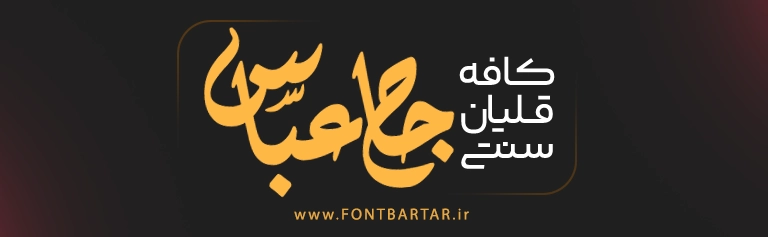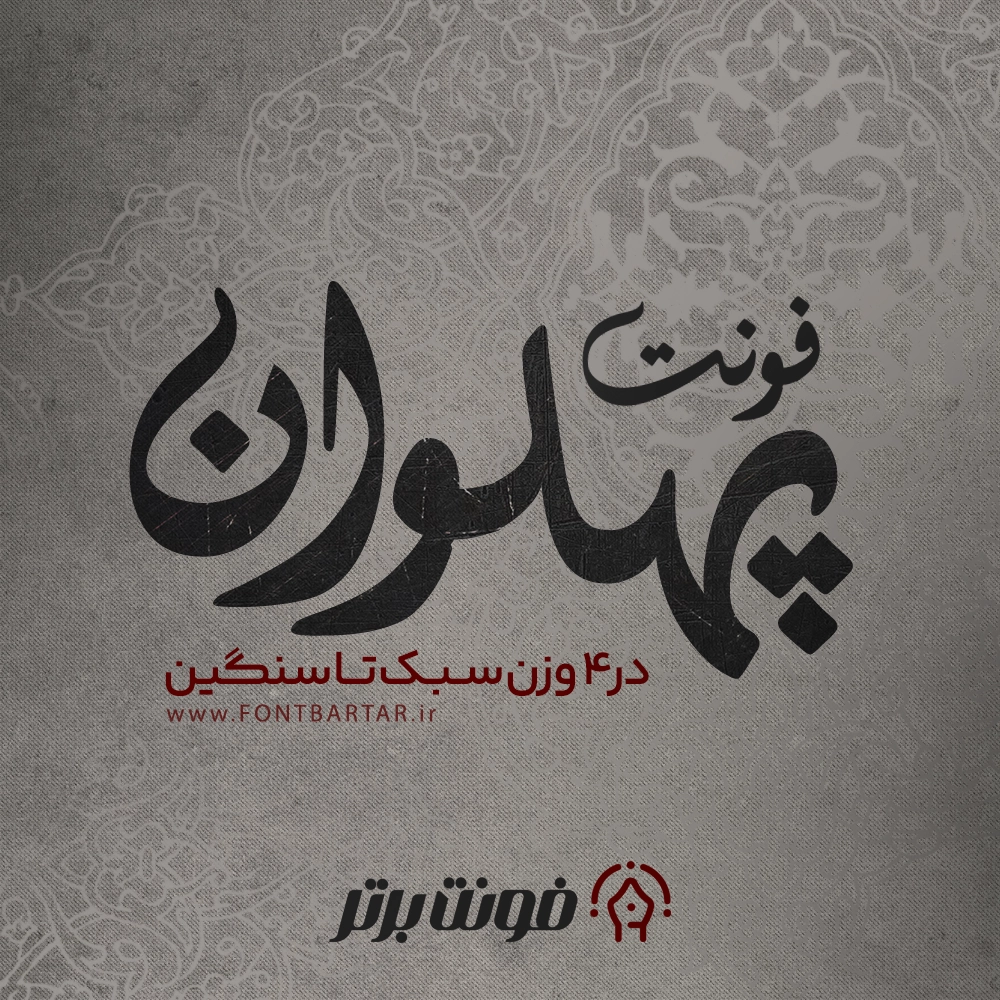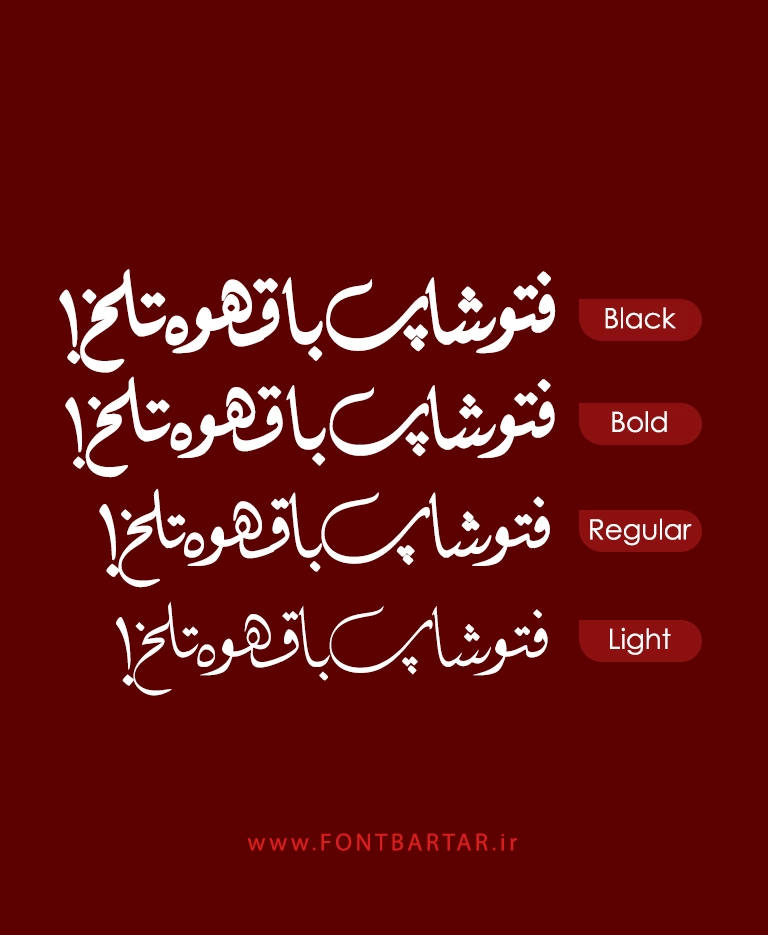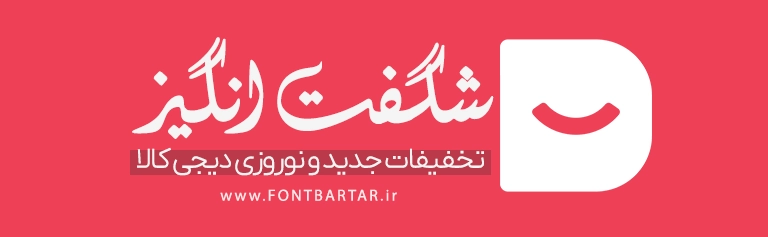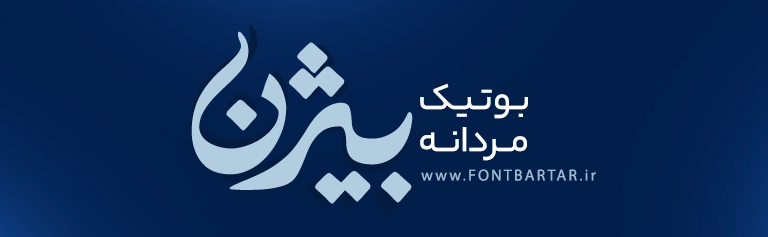
دانلود فونت فارسی پهلوان | فونت نستعیلق و زیبا برای طراحی خاص
فونت فارسی پهلوان یک فونت فارسی خاص ، سنگین و چشمگیر است که با الهام از تایپوگرافی سنتی و حس قدرت و صلابت طراحی شده است. فونت فارسی برای فتوشاپ انتخابی عالی برای طراحانی است که به دنبال ایجاد حس اقتدار، اصالت و هویت قوی در پروژههای گرافیکی خود هستند. اگر قصد دارید در طراحی پوستر، کاور، تایپوگرافی یا برندینگ، توجه مخاطب را در اولین نگاه جلب کنید، فونت زیبا پهلوان یکی از بهترین گزینههاست.
معرفی کامل فونت پهلوان و سبک طراحی آن
خرید فونت فارسی پهلوان دارای ساختاری سنگین، پرقدرت و نمایشی است که بهخوبی برای پروژههای خاص و جسورانه کاربرد دارد. ترکیب خطوط ضخیم با فرمهای سنتی باعث شده این فونت حس حماسی و ماندگاری بالایی ایجاد کند.
خرید فونت ویژگی برجسته فونت پهلوان:
- طراحی الهامگرفته از تایپوگرافی سنتی فارسی
- مناسب تیترها و نوشتههای نمایشی
- فونت نستعلیق پهلوان خوانایی بالا در سایزهای بزرگ
- جلوه بسیار قوی در تایپوگرافی هنری
فونت جدید پهلوان در ۴ وزن سبک تا سنگین
دانلود فونت در ۴ وزن استاندارد ارائه شده است تا طراح بتواند بسته به نیاز پروژه، انتخاب دقیقتری داشته باشد. تنوع وزنها امکان استفاده در طراحیهای مختلف را فراهم میکند؛ از تیترهای سنگین تا نوشتههای شاخص.
کاربرد وزنها:
- تیتر و هدینگ پوستر
- تایپوگرافی هنری و مذهبی
- طراحی کاور شبکههای اجتماعی
- لوگوتایپ و هویت بصری برند
کاربردهای فونت فارسی پهلوان
فونت پهلوان انتخابی ایدهآل برای پروژههایی است که نیاز به حس قدرت و جدیت دارند:
- طراحی پوستر فرهنگی، مذهبی و حماسی
- تایپوگرافی نام و شعار
- طراحی لوگو و لوگوتایپ فارسی
- کاور اینستاگرام و بنر تبلیغاتی
- پروژههای چاپی و دیجیتال
چرا فونت نستعلیق پهلوان برای طراحان حرفهای مناسب است؟
دانلود فونت نستعلیق پهلوان به طراحان کمک میکند تا بدون نیاز به طراحی دستی حروف، به یک فونت آماده با هویت بصری قوی دسترسی داشته باشند. این موضوع باعث صرفهجویی در زمان و افزایش کیفیت خروجی نهایی میشود.
مزایای اصلی فونت نستعلیق :
- سرعت بالا در طراحی
- جلوه حرفهای و متفاوت
FAQ – سوالات متداول درباره فونت پهلوان
❓ فونت پهلوان برای چه پروژههایی مناسب تر است؟
برای پوسترهای سنگین، تایپوگرافی نمایشی، طراحی مذهبی، فرهنگی و لوگوتایپ بسیار مناسب است.
❓ آیا فونت پهلوان خوانایی خوبی دارد؟
بله، این فونت مخصوص تیتر و نوشتههای بزرگ طراحی شده و در سایزهای بزرگ خوانایی بسیار بالایی دارد.